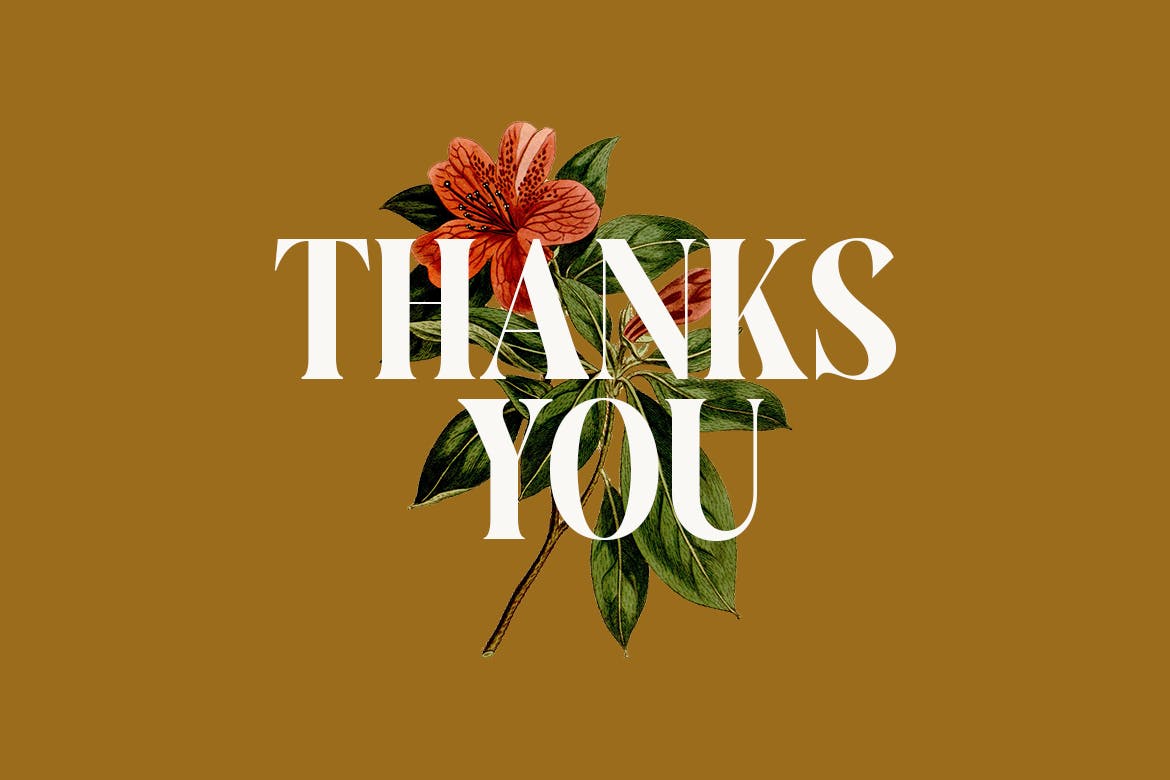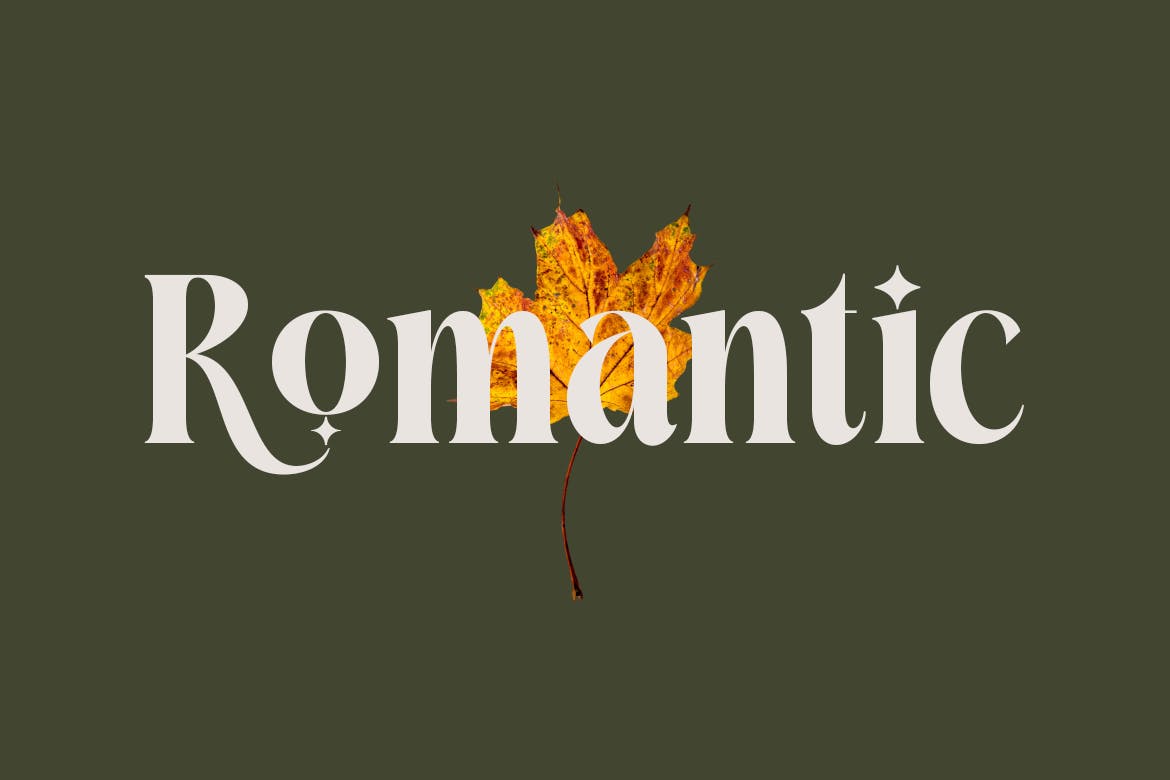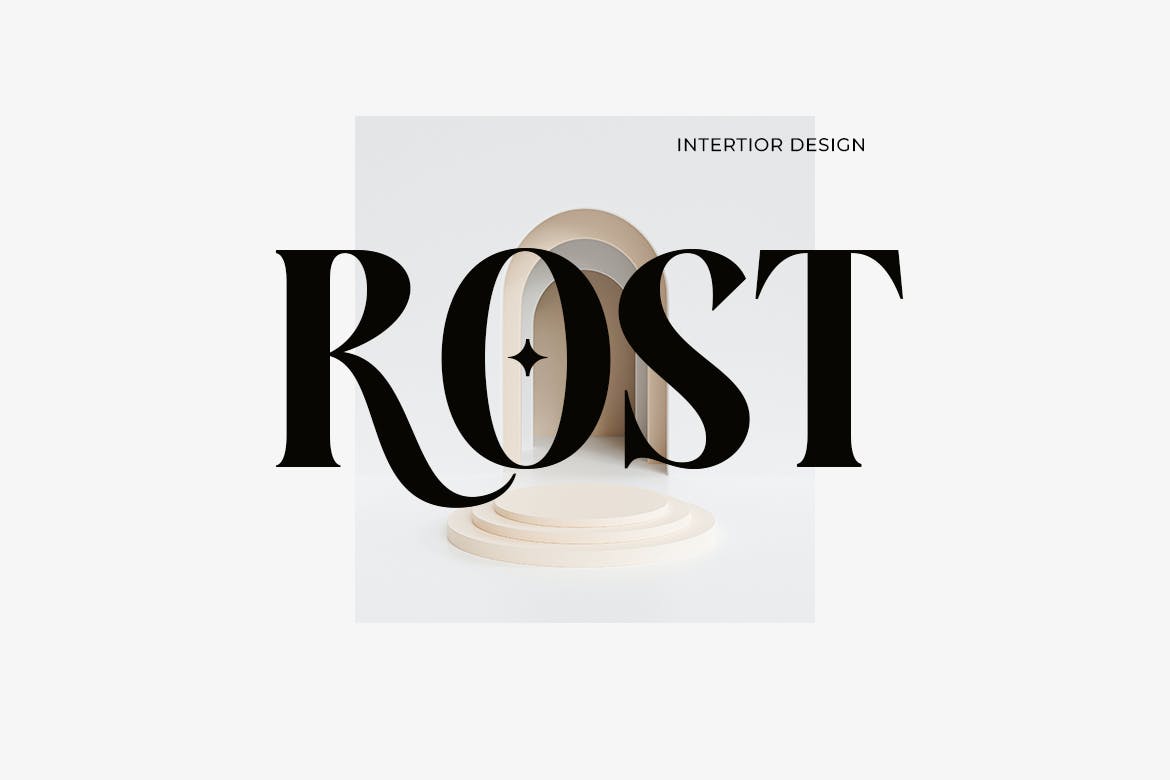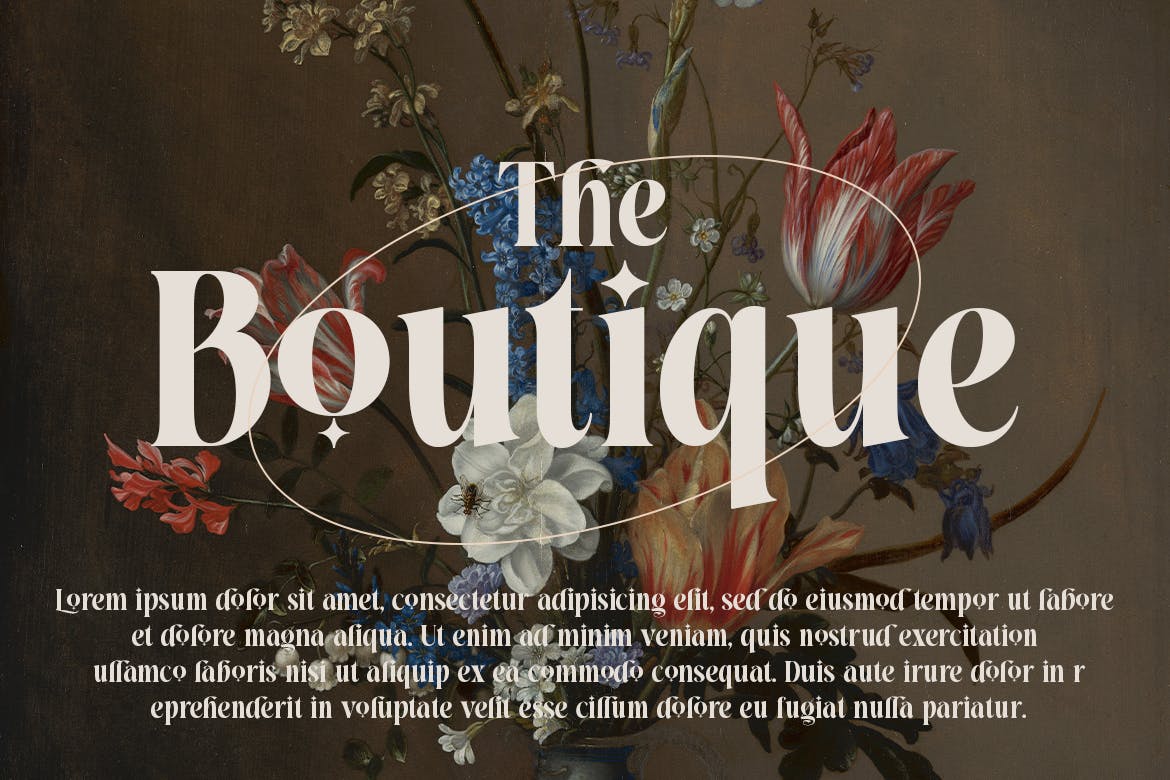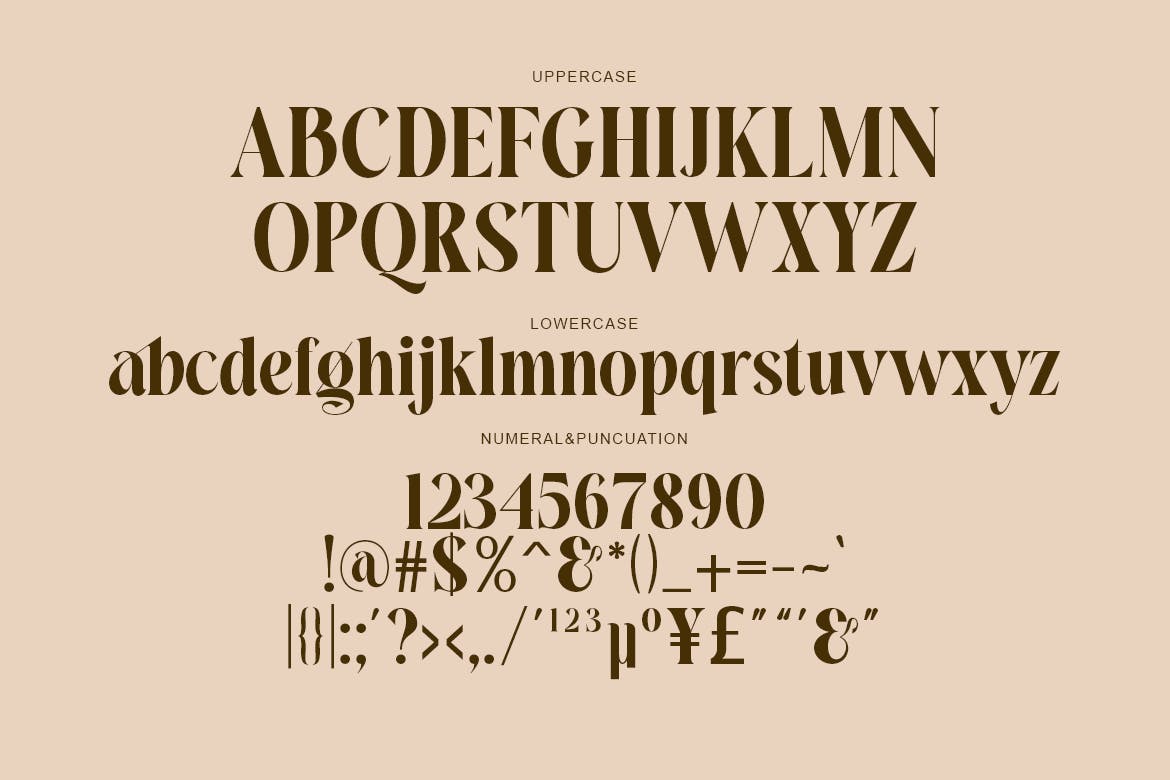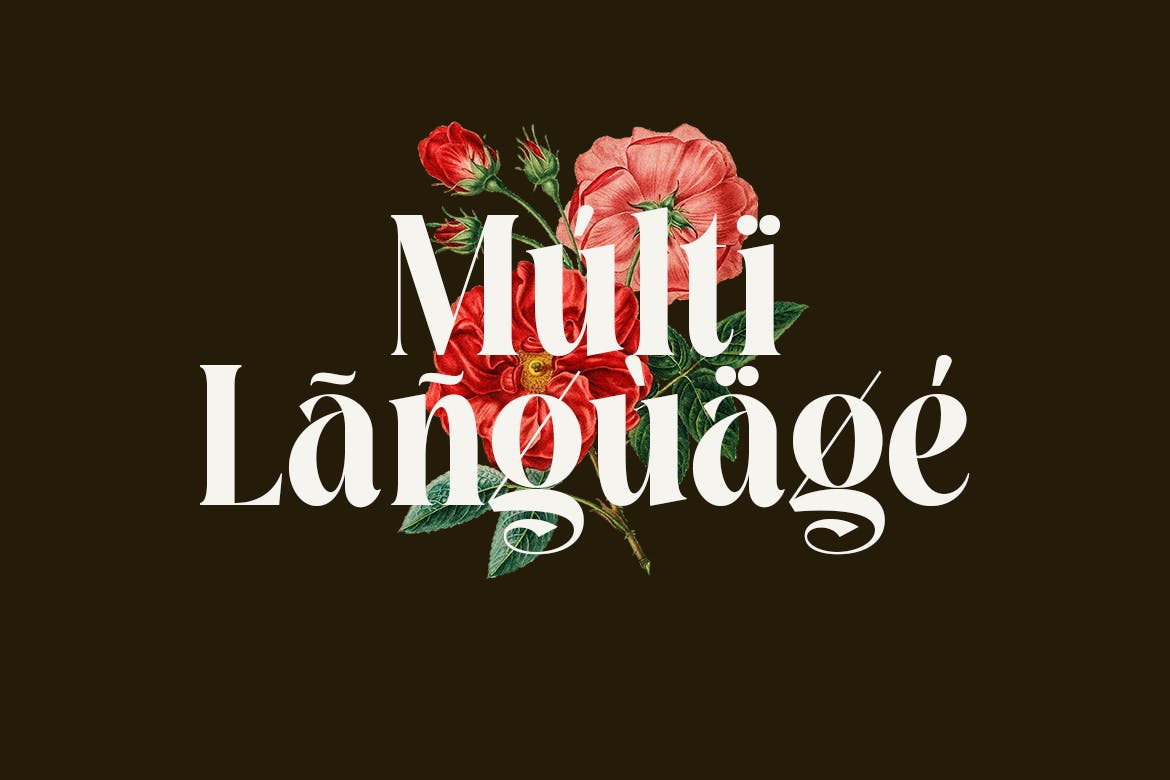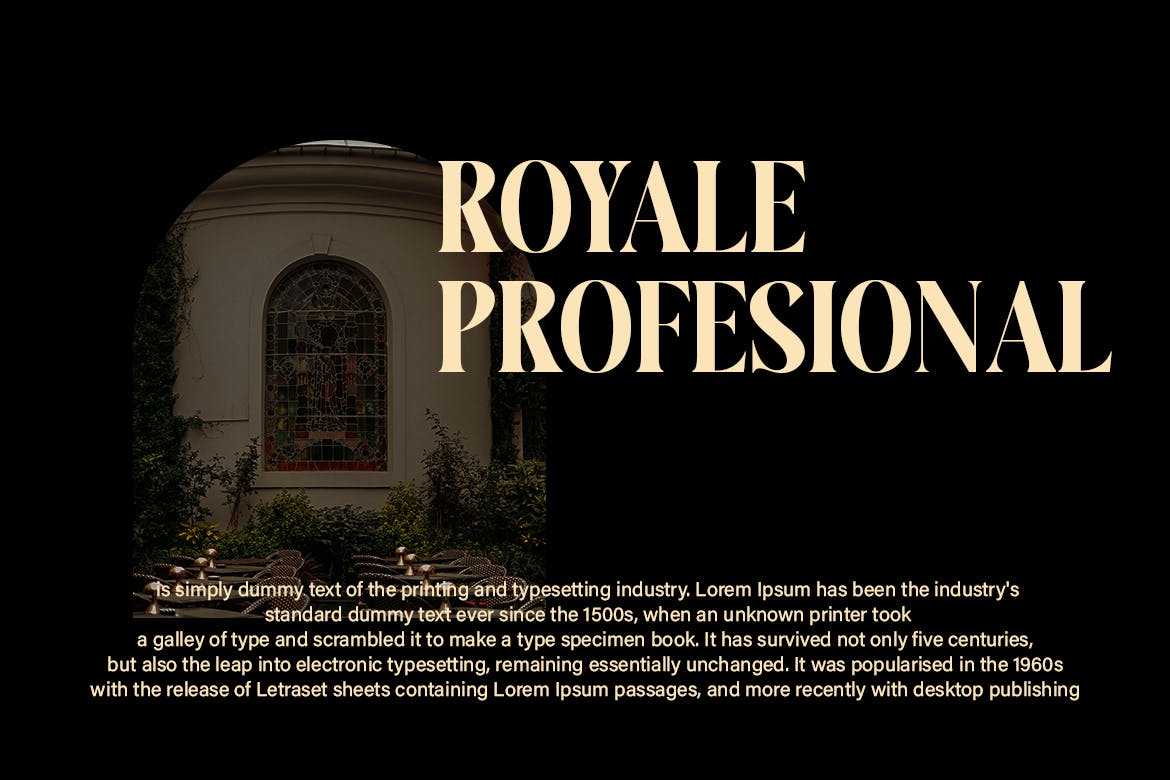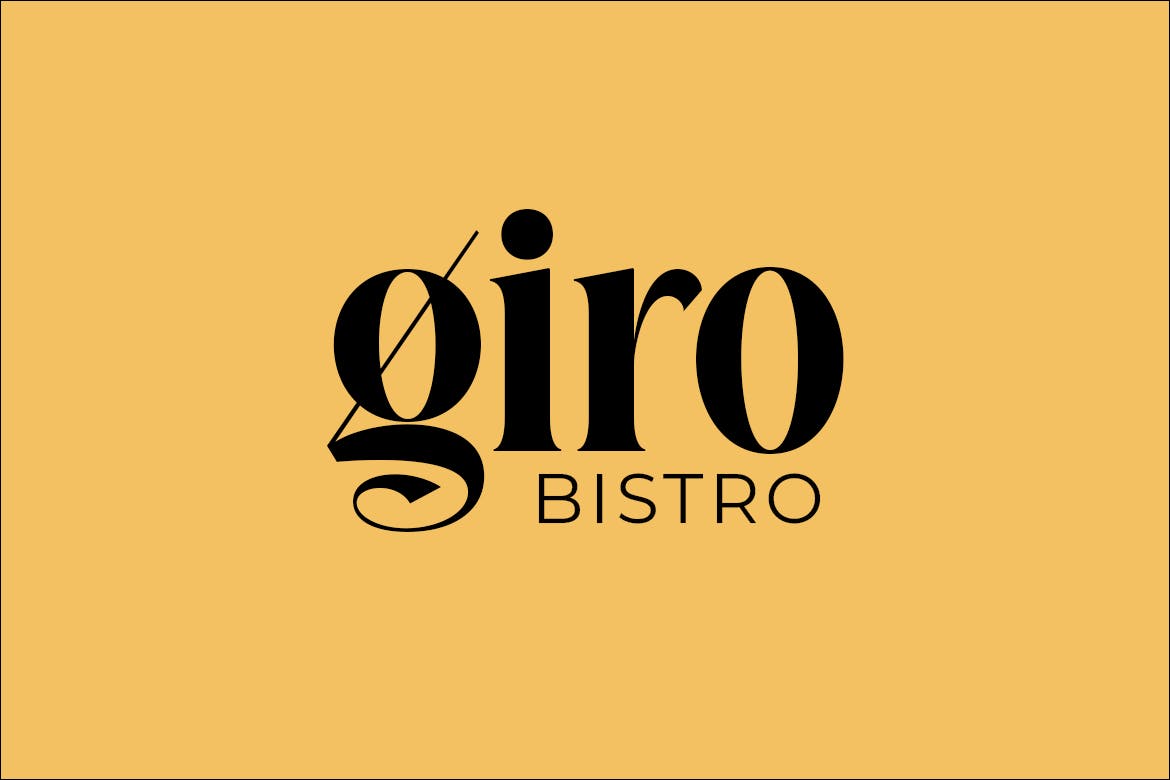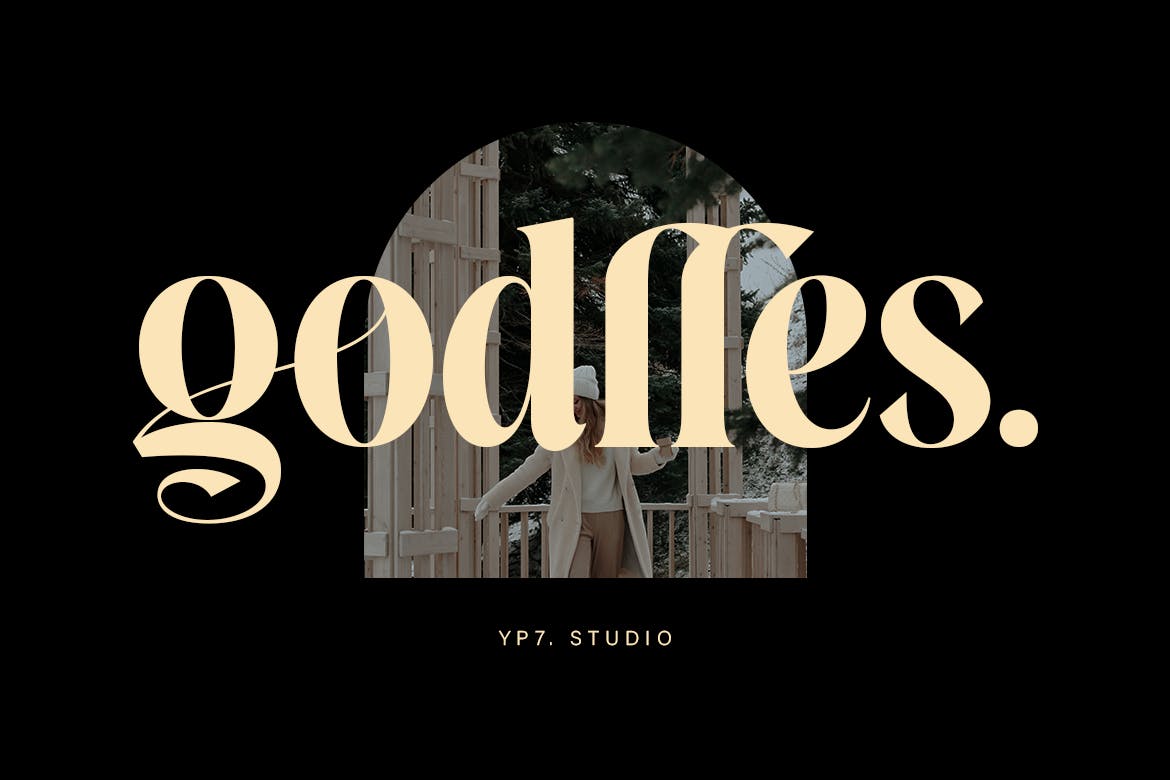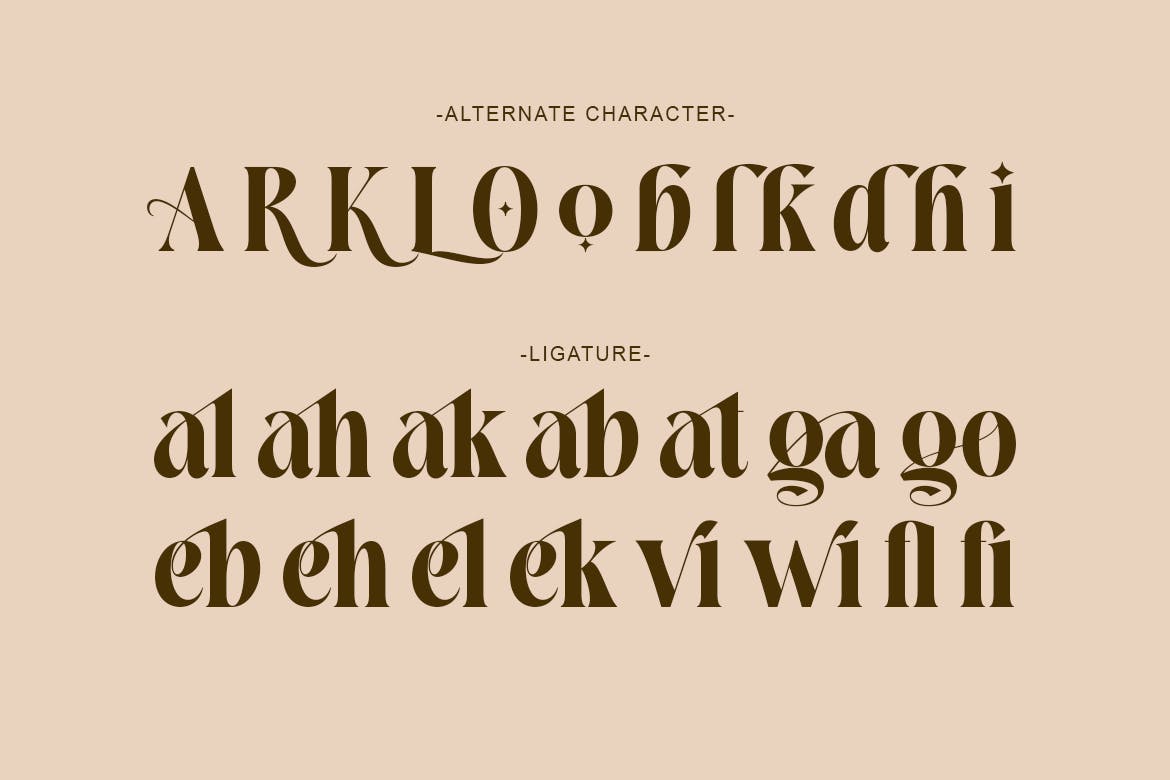
دانلود فونت سرسیک لوکس و شیک Arkosic
Elegant Luxury Serif Font
فونت Arkosic با طراحی زیبا و شیک، مناسب برای پروژههای طراحی شما.
فونت سرسیک لوکس و شیک Arkosic
حروف بزرگ
حروف کوچک
اعداد و نشانهگذاری